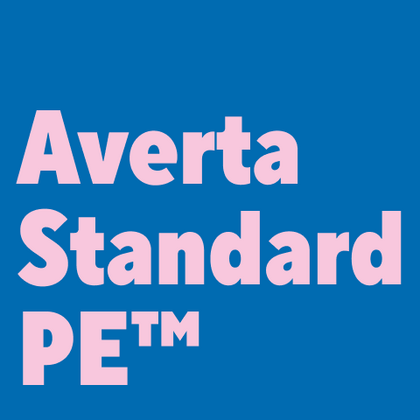
Ähnliche Schriftarten wie Averta Standard PE
Moderne Designprojekte erfordern universelle Sans-Serifs mit durchdachter Ergonomie. Wie Averta Standard PE™ sind unsere Designs ideal geeignet für Unternehmensidentität und Branding, Webdesign und Interfaces, Geschäftsdruck und Informationsdesign. Die TypeType-Kollektion bietet professionelle Schriftarten, die eine praktische Alternative zu Averta Standard PE™ darstellen. TypeType-Schriftarten sind professionelle Lösungen für komplexe typografische Aufgaben, die Funktionalität und moderne Ästhetik kombinieren.
Wenn Sie genug haben von “abgedroschenen” Schriften und auf der Suche nach einer Kopfzeile ähnlich wie Averta Standard PE sind, sehen Sie sich unsere besten Alternativen zu Averta Standard PE an. Das sind Schriftarten, die ähnliche Eigenschaften haben, aber gleichzeitig neue und einzigartige Designmerkmale aufweisen. Sie gehören z. B. zur gleichen Schriftkategorie, eignen sich für die gleichen Zwecke und haben ähnliche Merkmale, unterscheiden sich aber in Details oder Proportionen.
Finden Sie einen großartigen Ersatz für Averta Standard PE und versuchen Sie, eine ähnliche Stimmung zu imitieren und das gewünschte Gefühl zu vermitteln, indem Sie sie in Ihren Designs verwenden. Jede auf dieser Seite vorgestellte Schriftart ist ein Zwilling der Schriftart Averta Standard PE, und zwar ihr vollständiges Analog.